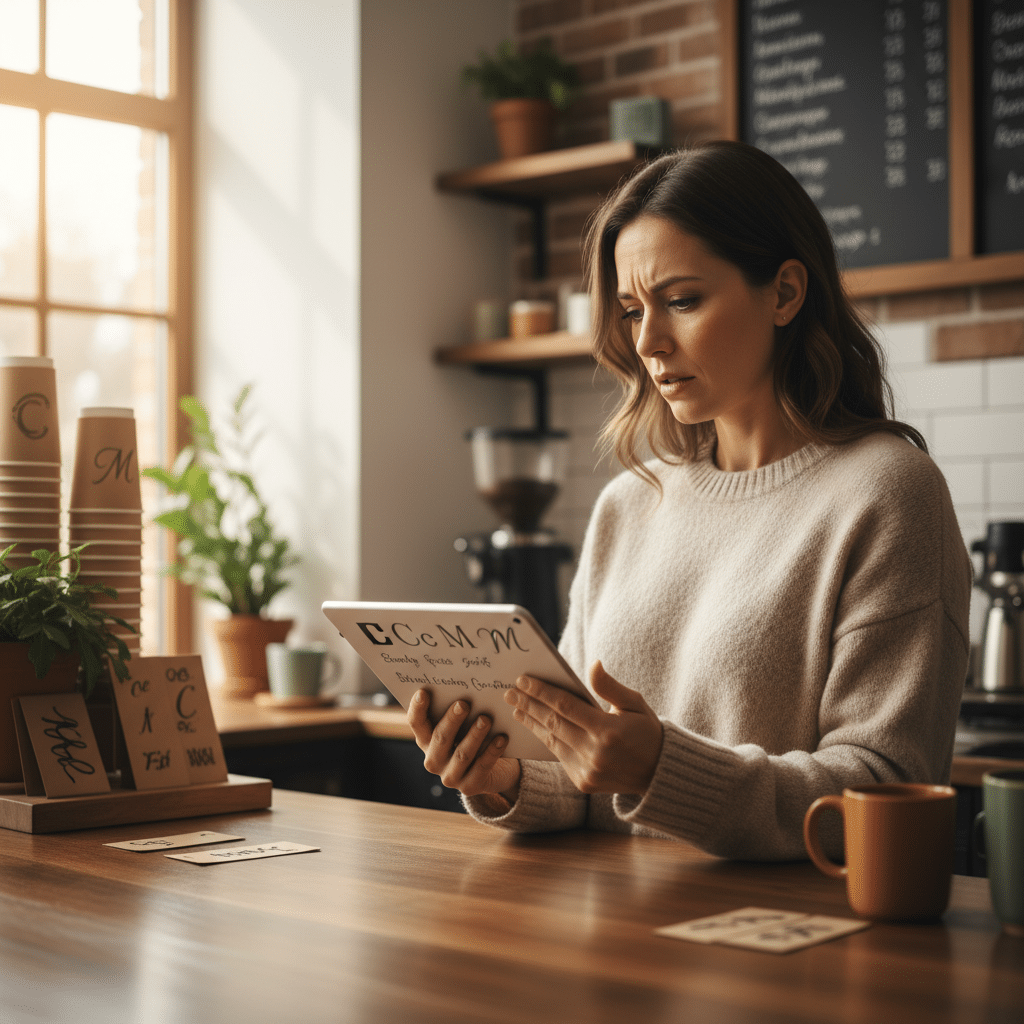
เลือกฟอนต์ผิด ชีวิตเปลี่ยน! จิตวิทยาฟอนต์สำหรับแบรนด์ SME
ในโลกของการสร้างแบรนด์สำหรับธุรกิจขนาดกลางและขนาดย่อม (SME) ทุกองค์ประกอบล้วนมีความสำคัญ ตั้งแต่โลโก้ไปจนถึงบรรจุภัณฑ์ แต่มีสิ่งหนึ่งที่มักถูกมองข้าม ทว่ากลับมีอิทธิพลต่อการรับรู้ของผู้บริโภคอย่างมหาศาล นั่นคือ “ฟอนต์” หรือรูปแบบตัวอักษร การเลือกใช้ฟอนต์จึงไม่ใช่แค่เรื่องของความสวยงาม แต่เป็นศาสตร์และศิลป์ที่เกี่ยวข้องกับจิตวิทยาโดยตรง
- ฟอนต์เป็นเครื่องมือสื่อสารบุคลิกภาพ ค่านิยม และสร้างการรับรู้ของแบรนด์โดยไม่ต้องใช้คำพูด
- ฟอนต์แต่ละประเภท เช่น Serif, Sans-serif และ Script สามารถกระตุ้นการตอบสนองทางอารมณ์และความรู้สึกที่แตกต่างกันในกลุ่มผู้บริโภค
- การเลือกฟอนต์ที่สอดคล้องกับตัวตนของแบรนด์จะช่วยเพิ่มความน่าเชื่อถือ ความโดดเด่น และสร้างความได้เปรียบในการแข่งขัน
- เทคนิคการจับคู่ฟอนต์ การเลือกใช้สี และความเข้าใจเรื่องลิขสิทธิ์ เป็นปัจจัยสำคัญที่ผู้ประกอบการ SME ไม่ควรมองข้ามเพื่อสร้างอัตลักษณ์ที่แข็งแกร่ง
ประโยคที่ว่า เลือกฟอนต์ผิด ชีวิตเปลี่ยน! จิตวิทยาฟอนต์สำหรับแบรนด์ SME ไม่ใช่คำกล่าวที่เกินจริง ในตลาดที่มีการแข่งขันสูง การตัดสินใจเลือกใช้รูปแบบตัวอักษรบนโลโก้ ฉลากสินค้า หรือสื่อส่งเสริมการขายต่างๆ สามารถส่งผลกระทบต่อภาพลักษณ์และความสำเร็จของธุรกิจได้อย่างไม่น่าเชื่อ ฟอนต์ทำหน้าที่เป็นเหมือน “เสื้อผ้า” ของแบรนด์ ที่สามารถบอกเล่าเรื่องราว สร้างความไว้วางใจ หรือแม้กระทั่งผลักไสลูกค้าออกไปได้หากเลือกใช้ไม่เหมาะสม บทความนี้จะเจาะลึกถึงหลักการของจิตวิทยาฟอนต์ (Font Psychology) เพื่อให้ผู้ประกอบการ SME เข้าใจถึงพลังที่ซ่อนอยู่ในตัวอักษร และสามารถนำไปปรับใช้เพื่อสร้างแบรนด์ที่แข็งแกร่งและน่าจดจำ
ทำไมการเลือกฟอนต์ถึงมีความสำคัญอย่างยิ่งต่อธุรกิจ SME?
สำหรับธุรกิจ SME ที่ทรัพยากรและงบประมาณอาจมีจำกัด การสร้างความประทับใจแรก (First Impression) ที่ดีที่สุดเป็นสิ่งสำคัญอย่างยิ่ง ฟอนต์คือหนึ่งในองค์ประกอบด่านแรกที่ลูกค้าจะได้สัมผัสกับแบรนด์ ไม่ว่าจะผ่านทางออนไลน์หรือออฟไลน์ การเลือกฟอนต์จึงเป็นมากกว่าการตัดสินใจด้านการออกแบบ แต่เป็นการวางรากฐานเชิงกลยุทธ์ให้กับแบรนด์
ผู้ประกอบการ SME คือกลุ่มที่ควรให้ความสำคัญกับเรื่องนี้เป็นพิเศษ เพราะฟอนต์ที่เลือกใช้จะสะท้อนถึงความเป็นมืออาชีพ ความน่าเชื่อถือ และตำแหน่งทางการตลาดของแบรนด์ได้ทันที ฟอนต์ที่ดูไม่เป็นทางการหรืออ่านยากอาจทำให้ลูกค้ารู้สึกว่าแบรนด์ขาดความน่าเชื่อถือ ในทางกลับกัน ฟอนต์ที่เลือกมาอย่างดีจะช่วยยกระดับสินค้าหรือบริการให้ดูมีมูลค่าสูงขึ้น สร้างความแตกต่างจากคู่แข่ง และสื่อสารกับกลุ่มเป้าหมายได้อย่างตรงจุด การลงทุนเวลาเพื่อทำความเข้าใจและเลือกฟอนต์ที่เหมาะสมจึงเป็นการลงทุนที่คุ้มค่าในระยะยาว ช่วยให้แบรนด์เป็นที่จดจำและสร้างความสัมพันธ์อันดีกับลูกค้าได้ตั้งแต่แรกเห็น
ถอดรหัสความรู้สึกผ่านตัวอักษร: จิตวิทยาฟอนต์คืออะไร?
จิตวิทยาฟอนต์ หรือ Font Psychology คือการศึกษาว่ารูปแบบตัวอักษรต่างๆ ส่งผลต่อความคิด ความรู้สึก และการรับรู้ของมนุษย์อย่างไร โดยแนวคิดนี้ตั้งอยู่บนพื้นฐานที่ว่ารูปทรง เส้นสาย ความหนาบาง และความโค้งมนของตัวอักษรสามารถกระตุ้นการตอบสนองทางอารมณ์และจิตใต้สำนึกที่แตกต่างกันได้ ฟอนต์จึงไม่ใช่เพียงพาหะในการนำเสนอข้อมูล แต่เป็นเครื่องมืออันทรงพลังในการสื่อสาร “บุคลิกภาพ” ของแบรนด์ไปยังผู้บริโภค
เมื่อผู้บริโภคเห็นฟอนต์ สมองจะประมวลผลและเชื่อมโยงลักษณะทางกายภาพของฟอนต์เข้ากับคุณลักษณะหรือประสบการณ์ที่เคยพบเจอโดยอัตโนมัติ ตัวอย่างเช่น ฟอนต์ที่มีเส้นสายแข็งแรงและมั่นคงอาจถูกเชื่อมโยงกับความแข็งแกร่งและความน่าเชื่อถือ ในขณะที่ฟอนต์ที่มีความโค้งมนและลื่นไหลอาจให้ความรู้สึกถึงความอ่อนโยน ความคิดสร้างสรรค์ หรือความเป็นมิตร การทำความเข้าใจหลักการนี้ช่วยให้นักออกแบบและเจ้าของแบรนด์สามารถเลือกใช้ฟอนต์เพื่อสร้างอารมณ์และความรู้สึกที่ต้องการให้เกิดขึ้นกับกลุ่มเป้าหมายได้อย่างแม่นยำ
ฟอนต์คือภาษากายของแบรนด์ มันบอกเล่าเรื่องราวว่าแบรนด์ของคุณเป็นใครก่อนที่ลูกค้าจะได้อ่านข้อความแม้แต่คำเดียว
พลังของฟอนต์ในการสร้างการรับรู้ของแบรนด์
ผลกระทบของฟอนต์ต่อการรับรู้แบรนด์นั้นได้รับการยืนยันจากการวิจัยหลายชิ้น การศึกษาโดย Monotype ซึ่งเป็นบริษัทชั้นนำด้านไทโปกราฟี พบว่าฟอนต์มีอิทธิพลโดยตรงต่อการรับรู้ในด้านต่างๆ ของผู้บริโภคอย่างมีนัยสำคัญ
ตัวอย่างที่ชัดเจนคือการใช้ฟอนต์ Gilroy Bold ซึ่งจัดอยู่ในประเภท Geometric Sans-serif (ฟอนต์ไม่มีเชิงเรขาคณิต) การวิจัยพบว่าฟอนต์นี้สามารถเพิ่มการรับรู้ถึง ความซื่อสัตย์ (Honesty) ของแบรนด์ได้ถึง 5% สร้างความรู้สึกว่าเป็นของแท้ น่าเชื่อถือ และประสบความสำเร็จ นอกจากนี้ แบรนด์ที่ใช้ฟอนต์ลักษณะนี้ยังถูกมองว่ามี นวัตกรรม (Innovation) เพิ่มขึ้น 9% และมีความ โดดเด่น (Distinctiveness) เพิ่มขึ้น 7% ทำให้ฟอนต์ประเภทนี้เป็นที่นิยมในกลุ่มแบรนด์เทคโนโลยีและสตาร์ทอัพสมัยใหม่
ในทางตรงกันข้าม ฟอนต์ในกลุ่ม Languid Serifs อย่าง Cotford ซึ่งเป็นฟอนต์มีเชิงที่ดูนุ่มนวลและสง่างาม กลับสร้างการรับรู้ที่แตกต่างออกไป ฟอนต์ประเภทนี้สื่อถึง คุณภาพที่สูง (High Quality) ความน่าเชื่อถือ และความหรูหรา จึงมักถูกนำไปใช้กับแบรนด์แฟชั่นระดับไฮเอนด์ สินค้าอุปโภคบริโภคระดับพรีเมียม หรือธุรกิจที่ต้องการสร้างภาพลักษณ์ของความประณีตและน่าไว้วางใจ
ข้อมูลเหล่านี้ชี้ให้เห็นว่าการเลือกฟอนต์ไม่ใช่เรื่องของรสนิยมส่วนตัว แต่เป็นเครื่องมือเชิงกลยุทธ์ที่สามารถกำหนดทิศทางการรับรู้ของแบรนด์ในใจผู้บริโภคได้โดยตรง
สำรวจโลกของฟอนต์: ทำความรู้จัก 3 ประเภทหลักสำหรับแบรนด์
เพื่อที่จะเลือกฟอนต์ได้อย่างเหมาะสม การทำความเข้าใจการจำแนกประเภท (Classification) ของฟอนต์เป็นสิ่งแรกที่ควรเรียนรู้ โดยทั่วไปแล้ว ฟอนต์สามารถแบ่งออกได้เป็นหลายประเภท แต่สำหรับผู้ประกอบการ SME การทำความเข้าใจ 3 ประเภทหลักก็เพียงพอที่จะสร้างความแตกต่างได้อย่างมหาศาล
ฟอนต์มีเชิง (Serif) – สัญลักษณ์แห่งความน่าเชื่อถือและความคลาสสิก
ฟอนต์ประเภท Serif มีลักษณะเด่นคือมี “เชิง” หรือ “ขีด” เล็กๆ ประดับอยู่ที่ปลายสุดของเส้นตัวอักษร ซึ่งเป็นรูปแบบที่มีมาแต่ดั้งเดิมและพบเห็นได้บ่อยในสื่อสิ่งพิมพ์ เช่น หนังสือพิมพ์และนิตยสาร เชิงเหล่านี้ช่วยนำสายตาของผู้อ่าน ทำให้การอ่านข้อความยาวๆ ทำได้ง่ายขึ้นในสื่อสิ่งพิมพ์
ในเชิงจิตวิทยา ฟอนต์ Serif มักสื่อถึงความ คลาสสิก, ความน่าเชื่อถือ, ประเพณี, ความเป็นทางการ และความสง่างาม แบรนด์ที่ต้องการสร้างภาพลักษณ์ที่มั่นคง มีประวัติศาสตร์ยาวนาน หรือเน้นคุณภาพระดับสูง มักจะเลือกใช้ฟอนต์ประเภทนี้ ตัวอย่างเช่น แบรนด์สินค้าหรูหรา สถาบันการเงิน สำนักกฎหมาย หรือมหาวิทยาลัย
ฟอนต์ไม่มีเชิง (Sans-serif) – ภาพลักษณ์ของความทันสมัยและเป็นมิตร
“Sans” เป็นภาษาฝรั่งเศสแปลว่า “ไม่มี” ดังนั้น Sans-serif จึงหมายถึงฟอนต์ที่ “ไม่มีเชิง” ที่ปลายตัวอักษร ทำให้มีรูปลักษณ์ที่ดูสะอาด เรียบง่าย และทันสมัย ฟอนต์ประเภทนี้ได้รับความนิยมอย่างสูงในยุคดิจิทัล เนื่องจากอ่านง่ายบนหน้าจอคอมพิวเตอร์และโทรศัพท์มือถือที่มีความละเอียดแตกต่างกัน
ฟอนต์ Sans-serif สื่อถึงความ ทันสมัย, ความเรียบง่าย, ความเป็นมิตร, ความตรงไปตรงมา และนวัตกรรม จึงเหมาะอย่างยิ่งสำหรับแบรนด์เทคโนโลยี, สตาร์ทอัพ, แบรนด์แฟชั่นสตรีทแวร์ หรือธุรกิจที่ต้องการสื่อสารกับกลุ่มคนรุ่นใหม่ที่เน้นความชัดเจนและเข้าถึงง่าย ฟอนต์ตระกูลย่อยในกลุ่มนี้ เช่น Geometric (ทรงเรขาคณิต) หรือ Humanist (มีความโค้งมนคล้ายลายมือ) ก็ให้ความรู้สึกที่แตกต่างกันไปอีก
ฟอนต์ลายมือ (Script) – สัมผัสแห่งความคิดสร้างสรรค์และความอบอุ่น
ฟอนต์ประเภท Script เลียนแบบลายมือเขียนที่มีความต่อเนื่องและลื่นไหล มีตั้งแต่รูปแบบที่เป็นทางการและสง่างาม ไปจนถึงรูปแบบที่ดูสบายๆ และเป็นกันเอง
ฟอนต์ Script มักจะกระตุ้นความรู้สึก อบอุ่น, ความคิดสร้างสรรค์, ความเป็นส่วนตัว, ความหรูหรา และความเป็นผู้หญิง อย่างไรก็ตาม เนื่องจากความซับซ้อนของเส้นสาย ฟอนต์ประเภทนี้อาจอ่านได้ยากหากใช้กับข้อความยาวๆ จึงนิยมใช้ในส่วนที่เป็นหัวข้อ โลโก้ หรือข้อความสั้นๆ ที่ต้องการเน้นเป็นพิเศษ แบรนด์ที่เหมาะกับฟอนต์นี้ ได้แก่ ร้านเบเกอรี่, แบรนด์สินค้าแฮนด์เมด, ช่างภาพ หรือธุรกิจที่ต้องการสร้างความรู้สึกใกล้ชิดและเป็นกันเองกับลูกค้า
| คุณสมบัติ | ฟอนต์มีเชิง (Serif) | ฟอนต์ไม่มีเชิง (Sans-serif) | ฟอนต์ลายมือ (Script) |
|---|---|---|---|
| บุคลิกภาพ/อารมณ์ | น่าเชื่อถือ, คลาสสิก, เป็นทางการ, สง่างาม, ภูมิฐาน | ทันสมัย, เรียบง่าย, เป็นมิตร, ชัดเจน, มีนวัตกรรม | สร้างสรรค์, อบอุ่น, เป็นส่วนตัว, หรูหรา, อ่อนโยน |
| เหมาะสำหรับแบรนด์ | สถาบันการเงิน, สำนักกฎหมาย, แบรนด์หรู, สินค้าคุณภาพสูง, สำนักพิมพ์ | บริษัทเทคโนโลยี, สตาร์ทอัพ, แบรนด์แฟชั่นสมัยใหม่, ธุรกิจบริการที่เน้นความรวดเร็ว | ร้านอาหาร/คาเฟ่, สินค้าแฮนด์เมด, การ์ดเชิญ, แบรนด์ที่เน้นความเป็นผู้หญิง |
| การใช้งานที่แนะนำ | เนื้อหาขนาดยาวในสื่อสิ่งพิมพ์, โลโก้ที่ต้องการความภูมิฐาน, หัวข้อที่ต้องการความน่าเชื่อถือ | เนื้อหาบนเว็บไซต์และแอปพลิเคชัน, โลโก้ที่ต้องการความทันสมัย, ป้ายและสื่อประชาสัมพันธ์ | โลโก้, หัวข้อสั้นๆ, ข้อความเน้นอารมณ์, ลายเซ็น, บรรจุภัณฑ์ |
| ข้อควรระวัง | อาจดูเก่าหรืออนุรักษ์นิยมเกินไปสำหรับบางแบรนด์, บางฟอนต์อ่านยากบนหน้าจอความละเอียดต่ำ | อาจดูเรียบง่ายหรือขาดเอกลักษณ์หากเลือกฟอนต์ที่ไม่โดดเด่นพอ | อ่านยากในขนาดเล็กและเมื่อใช้กับข้อความยาว, ควรใช้ในปริมาณที่จำกัด |
กลยุทธ์การเลือกและใช้งานฟอนต์เพื่อสร้างแบรนด์ที่น่าจดจำ
หลังจากทำความเข้าใจประเภทของฟอนต์แล้ว ขั้นตอนต่อไปคือการนำความรู้มาประยุกต์ใช้ในการสร้างแบรนด์ การเลือกฟอนต์ไม่ใช่การเลือกตามความชอบส่วนตัว แต่ต้องพิจารณาจากหลายปัจจัยประกอบกันเพื่อให้ได้ผลลัพธ์ที่ดีที่สุด
การเลือกฟอนต์สำหรับออกแบบโลโก้: สิ่งที่ SME ต้องรู้
โลโก้คือหน้าตาของแบรนด์ และฟอนต์ที่ใช้ในโลโก้คือองค์ประกอบสำคัญที่สุดอย่างหนึ่ง หลักการสำคัญในการเลือกฟอนต์สำหรับโลโก้ ได้แก่:
- ความชัดเจนในการอ่าน (Readability): ฟอนต์ต้องอ่านง่ายในทุกขนาด ไม่ว่าจะถูกย่อให้เล็กสำหรับนามบัตร หรือขยายใหญ่สำหรับป้ายโฆษณา ควรทดสอบฟอนต์ในขนาดต่างๆ เพื่อให้แน่ใจว่ายังคงอ่านออกได้ชัดเจน
- ความสอดคล้องกับบุคลิกแบรนด์: ฟอนต์ต้องสะท้อนถึงค่านิยมและบุคลิกภาพของแบรนด์ที่ต้องการสื่อสารออกไป หากเป็นแบรนด์ที่สนุกสนาน การใช้ฟอนต์ Serif ที่ดูเป็นทางการอาจไม่เหมาะสม
- ความเป็นเอกลักษณ์และน่าจดจำ: หลีกเลี่ยงการใช้ฟอนต์ที่พบเห็นได้ทั่วไปจนเกินไป เพราะจะทำให้แบรนด์ดูไม่โดดเด่นและไม่เป็นที่จดจำ การเลือกฟอนต์ที่มีเอกลักษณ์จะช่วยสร้างความแตกต่างจากคู่แข่งได้
เทคนิคการจับคู่ฟอนต์ (Font Pairing) เพื่อความสมดุล
ในการออกแบบสื่อต่างๆ ไม่ว่าจะเป็นเว็บไซต์, เมนูอาหาร หรือโบรชัวร์ มักจะมีการใช้ฟอนต์มากกว่าหนึ่งรูปแบบ เทคนิคการจับคู่ฟอนต์ (Font Pairing) จึงเข้ามามีบทบาทสำคัญเพื่อสร้างความสมดุลและลำดับชั้นทางสายตา (Visual Hierarchy) สูตรที่นิยมใช้กันคือ:
- ใช้ความแตกต่างอย่างลงตัว: จับคู่ฟอนต์ที่มีลักษณะแตกต่างกันอย่างชัดเจน เช่น การใช้ฟอนต์ Serif สำหรับหัวข้อ (Heading) เพื่อสร้างความรู้สึกน่าเชื่อถือ และใช้ฟอนต์ Sans-serif สำหรับเนื้อหา (Body Text) เพื่อให้อ่านง่ายและทันสมัย การใช้ฟอนต์ที่คล้ายกันเกินไปอาจทำให้การออกแบบดูน่าเบื่อและไม่น่าสนใจ
- จำกัดจำนวนฟอนต์: โดยทั่วไปแล้ว ไม่ควรใช้ฟอนต์เกิน 2-3 รูปแบบในการออกแบบชิ้นงานหนึ่งชิ้น การใช้ฟอนต์มากเกินไปจะทำให้ดูสับสนและขาดความเป็นมืออาชีพ
- สร้างลำดับชั้น: ใช้ขนาด, ความหนา และรูปแบบ (เช่น ตัวหนา, ตัวเอียง) ของฟอนต์เพื่อสร้างลำดับความสำคัญของข้อมูล ทำให้ผู้อ่านรู้ว่าส่วนไหนคือหัวข้อหลัก หัวข้อย่อย และเนื้อหา
สีและฟอนต์: การผสมผสานที่ลงตัวเพื่อสื่อสารอารมณ์
สีเป็นอีกหนึ่งองค์ประกอบที่มีผลต่อจิตวิทยาเช่นกัน การผสมผสานระหว่างสีและฟอนต์สามารถเพิ่มพลังในการสื่อสารอารมณ์ของแบรนด์ได้อย่างมาก ตัวอย่างเช่น:
- Serif + สีโทนหรู: การใช้ฟอนต์ Serif คู่กับสีอย่างสีกรมท่า, สีเลือดหมู หรือสีทอง สามารถเสริมสร้างภาพลักษณ์ของความหรูหราและความน่าเชื่อถือได้เป็นอย่างดี
- Sans-serif + สีโทนสดใส: การจับคู่ฟอนต์ Sans-serif ที่ดูทันสมัยกับสีที่สดใส เช่น สีส้ม, สีฟ้า หรือสีเขียว จะช่วยสร้างความรู้สึกถึงพลังงาน ความคิดสร้างสรรค์ และการเข้าถึงง่าย
หลีกเลี่ยงกับดัก: ความเสี่ยงของฟอนต์ฟรีและปัญหาลิขสิทธิ์
แม้ว่าจะมีแหล่งดาวน์โหลดฟอนต์ฟรีมากมายบนอินเทอร์เน็ต แต่การนำมาใช้ในเชิงพาณิชย์นั้นมีความเสี่ยงสูง ผู้ประกอบการ SME ต้องตระหนักว่าฟอนต์จำนวนมากมีลิขสิทธิ์คุ้มครอง และการใช้งานโดยไม่ได้รับอนุญาตอาจนำไปสู่การถูกฟ้องร้องเรียกค่าเสียหายได้
ก่อนนำฟอนต์ใดๆ มาใช้งาน ควรตรวจสอบเงื่อนไขการอนุญาต (License) อย่างละเอียดเสมอ ฟอนต์ฟรีบางตัวอาจอนุญาตให้ใช้ส่วนตัวเท่านั้น แต่ห้ามใช้ในเชิงพาณิชย์ การลงทุนซื้อฟอนต์ที่มีลิขสิทธิ์ถูกต้อง หรือเลือกใช้ฟอนต์จากแหล่งที่น่าเชื่อถือซึ่งระบุเงื่อนไขชัดเจน (เช่น Google Fonts) เป็นทางเลือกที่ปลอดภัยและคุ้มค่ากว่าในระยะยาว ช่วยลดความเสี่ยงทางกฎหมายและสร้างความเป็นมืออาชีพให้กับแบรนด์
สรุป: สร้างความสำเร็จให้แบรนด์ด้วยการเลือกฟอนต์ที่ใช่
การเลือกฟอนต์ไม่ใช่เพียงรายละเอียดเล็กน้อยในการออกแบบ แต่เป็นการตัดสินใจเชิงกลยุทธ์ที่สามารถส่งผลกระทบต่อภาพลักษณ์และความสำเร็จของแบรนด์ SME ได้อย่างลึกซึ้ง จิตวิทยาฟอนต์แสดงให้เห็นว่ารูปแบบตัวอักษรแต่ละแบบสามารถสื่อสารบุคลิกภาพ กระตุ้นอารมณ์ และสร้างการรับรู้ที่แตกต่างกันในใจของผู้บริโภค ตั้งแต่ความน่าเชื่อถือของฟอนต์ Serif, ความทันสมัยของ Sans-serif ไปจนถึงความคิดสร้างสรรค์ของ Script
สำหรับผู้ประกอบการ SME การทำความเข้าใจในพลังของฟอนต์และนำไปใช้อย่างพิถีพิถันในการออกแบบโลโก้ ฉลากสินค้า สื่อสิ่งพิมพ์ และสื่อดิจิทัล จะช่วยสร้างอัตลักษณ์ของแบรนด์ที่แข็งแกร่ง โดดเด่น และน่าจดจำ การเลือกฟอนต์ที่ถูกต้องไม่เพียงแต่จะช่วยดึงดูดลูกค้าเป้าหมาย แต่ยังเป็นการวางรากฐานที่มั่นคงให้กับแบรนด์เพื่อการเติบโตในอนาคต